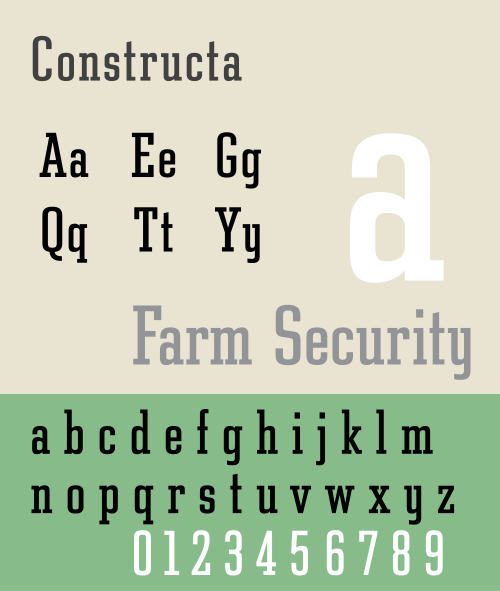
تاور (نوع الخط)
كان خط تاور خطًا ذا حروف مزخرفة مسطحة ، صممه موريس فولر بنتون لشركة أمريكان تايب فاوندرز ، واستند إلى تصميمه السابق لخط ستيمي ، لكن بجوانب مستقيمة للحروف الدائرية لتأكيد المظهر العمودي. صُمم خط تاور المائل ، لكن لم يُصنع منه. في عام 1936، بدأ المصمم نفسه العمل على خط تاور العريض ، لكنه تحول لاحقًا إلى خط ستيمي العريض المكثف. [ 1 ]
نوع رقمي
تمت رقمنة خط Tower ليصبح Constructa بواسطة إليزابيث كوري هولزمان لصالح Font Bureau . وتشمل نسخة هولزمان المُعاد تصميمها وزنًا خفيفًا يُسمى Constructa Thin ووزنًا عريضًا جدًا يُسمى Constructa Black .